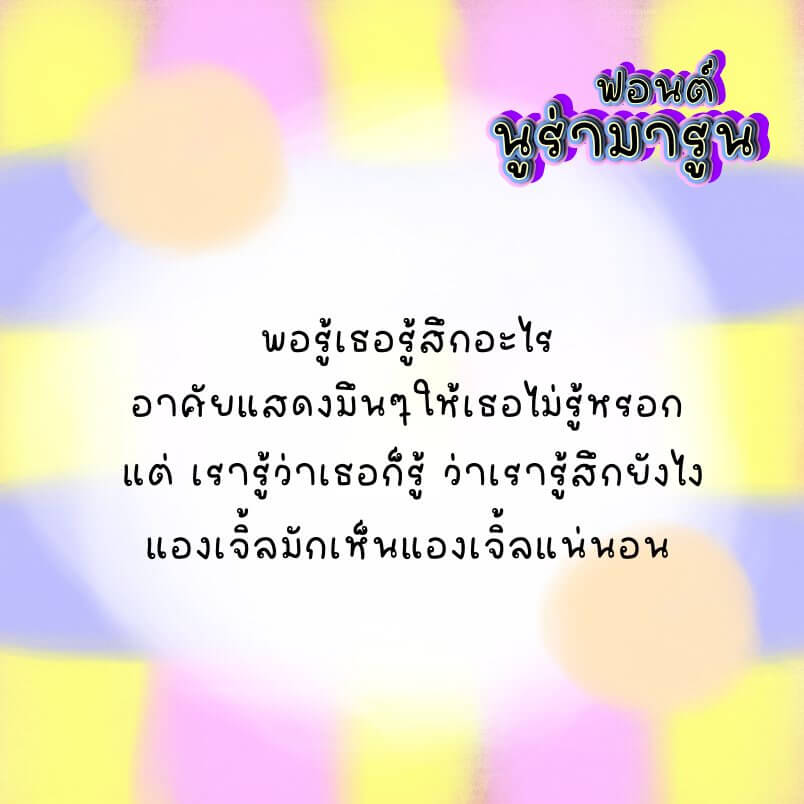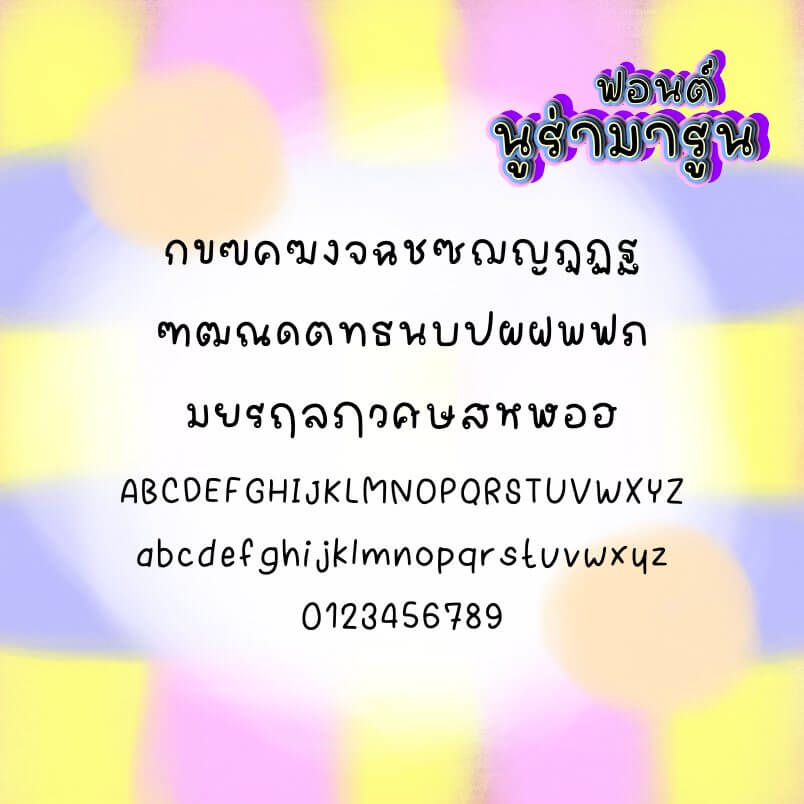
นูร่ามารูน (Nura maroon)
ฟอนต์ลายมือน่ารัก ตัวเล็กๆ หัวบางๆ อ่านง่าย เหมาะสำหรับเขียนโน้ต มีด้วยกัน 3 น้ำหนัก คือ บาง ปกติ หนา นูร่าราดาเปิดให้ใช้ฟรีงานส่วนตัวและงานทั่วไป น้ำหนักบาง